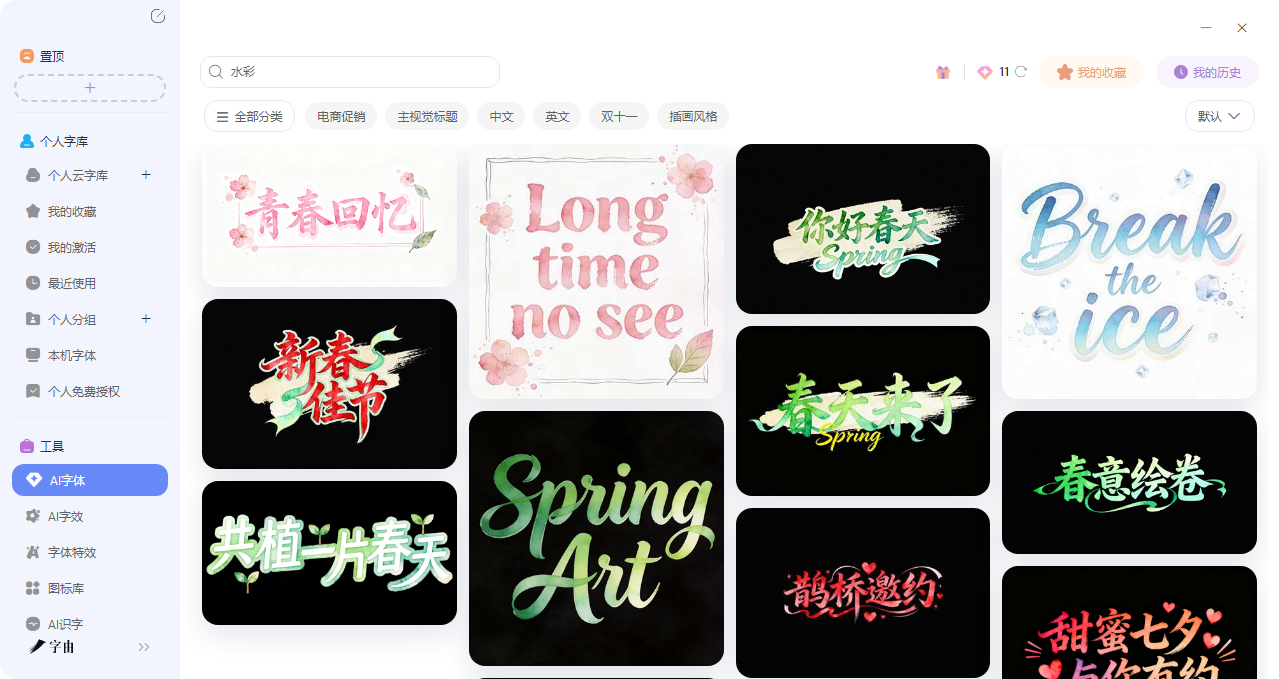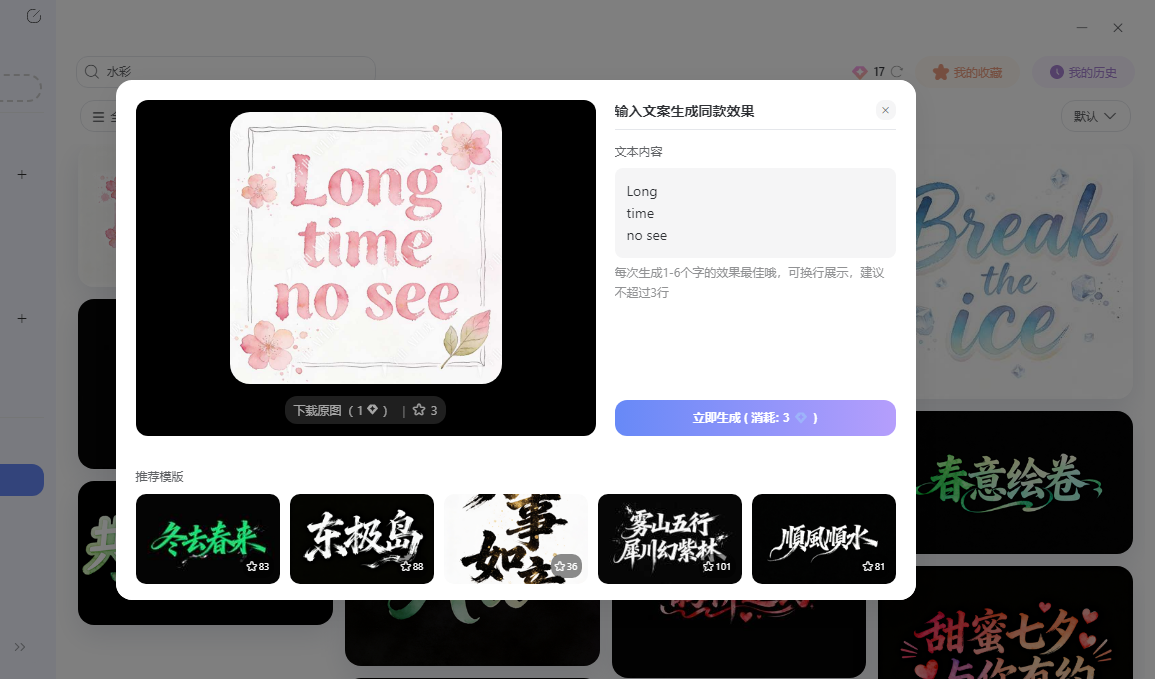
想要水彩感字体?试试这5个水彩风格文字设计工具
如果你经常做手账的话,肯定少不了一些水彩元素,这种像画在纸上的文字,总能让普通的画面多一层温度和质感。但是众所周知水彩字在纸面上容易写,但是怎么样才能转成电子版呢?自己画吧,没那个功底;找现成的吧,又怕版权不清。其实现在已经有很多水彩风格文字设计工具,能帮你一键生成这种效果。在这篇文章里我会推荐给大家5 个亲测好用的水彩风格文字设计工具,需要的可以收藏。
第一个要推荐的水彩风格文字设计工具是字由。除了本身拥有超过3500+款免费字体以外,字由还有很多实用的AI 工具,其中就包括AI 字体。它的“AI字体”功能,专门用来生成各种风格的艺术字,水彩效果当然也在其中。
下面是具体的生成步骤:
第一步:打开字由客户端,左侧导航栏找到【工具】→【AI字体】,或者从首页【字体工具】→【AI工具】进入。这个功能内置了大量艺术字模板,其中就有我们需要的水彩/手绘效果。
第二步:进入AI字体页面后,在搜索框里输入“水彩”“手绘”“晕染”“水痕”“手写感”等关键词,系统会自动筛选出所有带水彩质感的模板。你也可以直接点进“手写体”等分类里翻。
第三步:选择自己喜欢的模板,搜索结果会展示各种水彩风格的预览图,比如:
- 水彩晕染效果(边缘模糊,像颜料在纸上慢慢渗开)
- 湿笔触效果(带着水痕和笔触感)
- 干刷效果(像半干的画笔扫过纸面)
- 水彩肌理效果(能看见纸纹和颜料颗粒)
- 手绘水彩字(模仿真实手写的笔触)
每一个模板都有预览图,可以选择你喜欢的一个来生成。
第四步:点击选中的模板,进入编辑页面。在输入框里填你想要生成水彩效果的文字(比如“春日来信”“温柔以待”“手账时光”)。需要注意的是,可以看一下文字输入框的下面的提示词,每次生成1-6 个字的效果最佳!
第五步:确认文案后,点“立即生成”,等20-30秒左右,系统就会输出设计好的水彩艺术字图片。生成后可以预览效果,不满意就换其他模板再试。
这整个过程不超过五分钟,生成甚至不需要一分钟就可以做完了。如果你不满意,也可以去试试AI 字效或者是字体特效,都有足够丰富的模板库可供你选择!
2、FONTGET
我是直接在这个字体网站里搜索了“Watercolor”这个关键词,这样可以找到大量水彩风格的字体。它的分类逻辑很清晰,左侧有各种风格标签,方便筛选。
虽然这些不算严格意义上的水彩特效字体,但是这些字体的写法就能看出带着复古手写感,很适合做水彩效果。如果拿来作为设计的底层字体会非常合适,而且每款字体都标注了“100% Free”,可以放心下载。
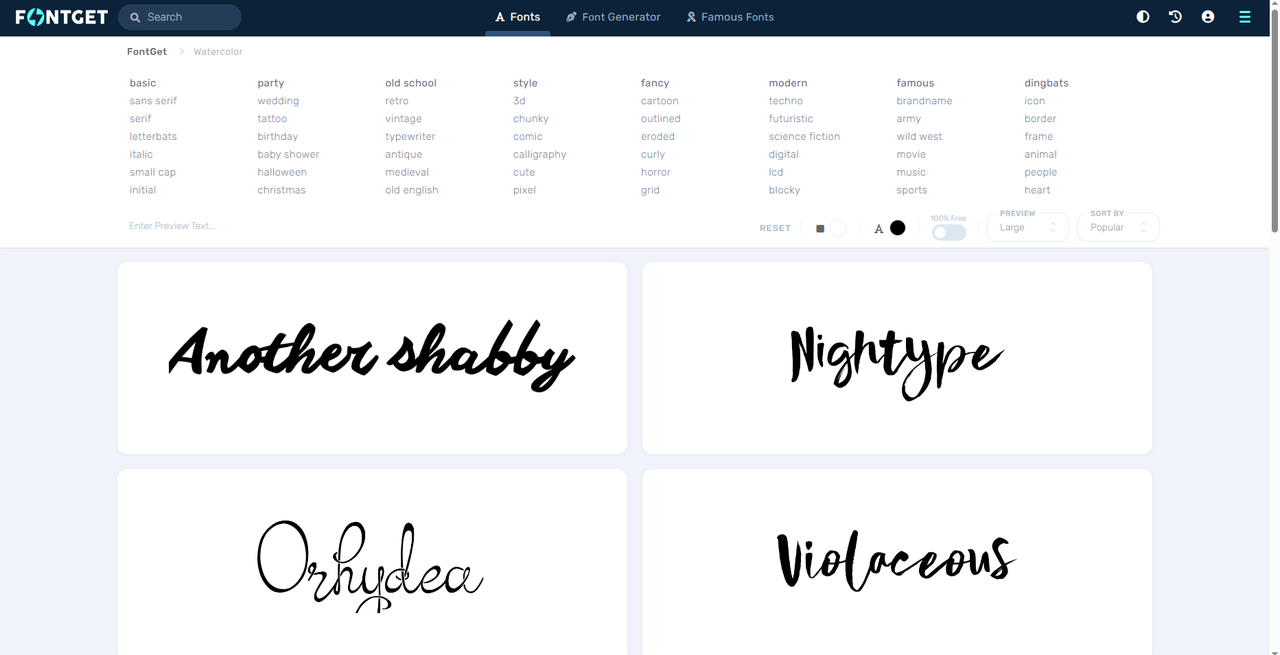
3、Envato Elements
Envato Elements 是一个专业的设计资源平台,它的水彩字体分类非常丰富。最主要的是这里的水彩字体不仅数量多,而且品质很高。我可以为大家推荐几款这里面质量比较高的水彩字体:
- Katie Roze Watercolor SVG Font:SVG格式的水彩字体,保留矢量特性的同时有水彩质感。
- Dayanara watercolor serif svg:衬线体的水彩版本,优雅温柔。
- Spring Rain:标注为“A TEXTURED BRUSH FONT”(带纹理的画笔字体),包含SVG和实心两个版本。
除了这几个之外,网站还提供了详细的筛选功能:可以按分类(Serif、Sans-Serif、Script)、字宽、最佳用途等筛选。虽然大部分是付费资源,但品质确实高,适合对水彩字体有专业需求的用户。
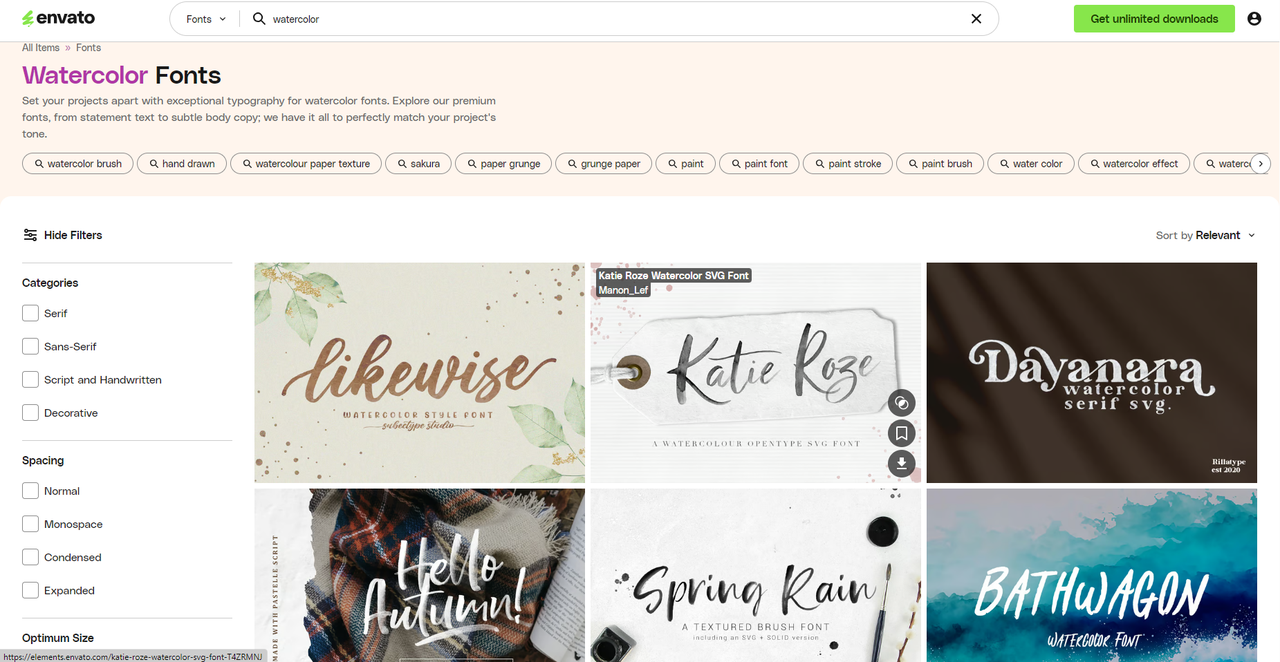
4、Creative Fabrica
Creative Fabrica 是一个创作者集市,收录了大量水彩风格字体,一共有2900+款水彩字体,网站支持预览功能,可以输入自己的文字,选择24pt/36pt/48pt/72pt等字号预览效果。虽然大部分需要付费,但偶尔有限免和折扣,可以关注。
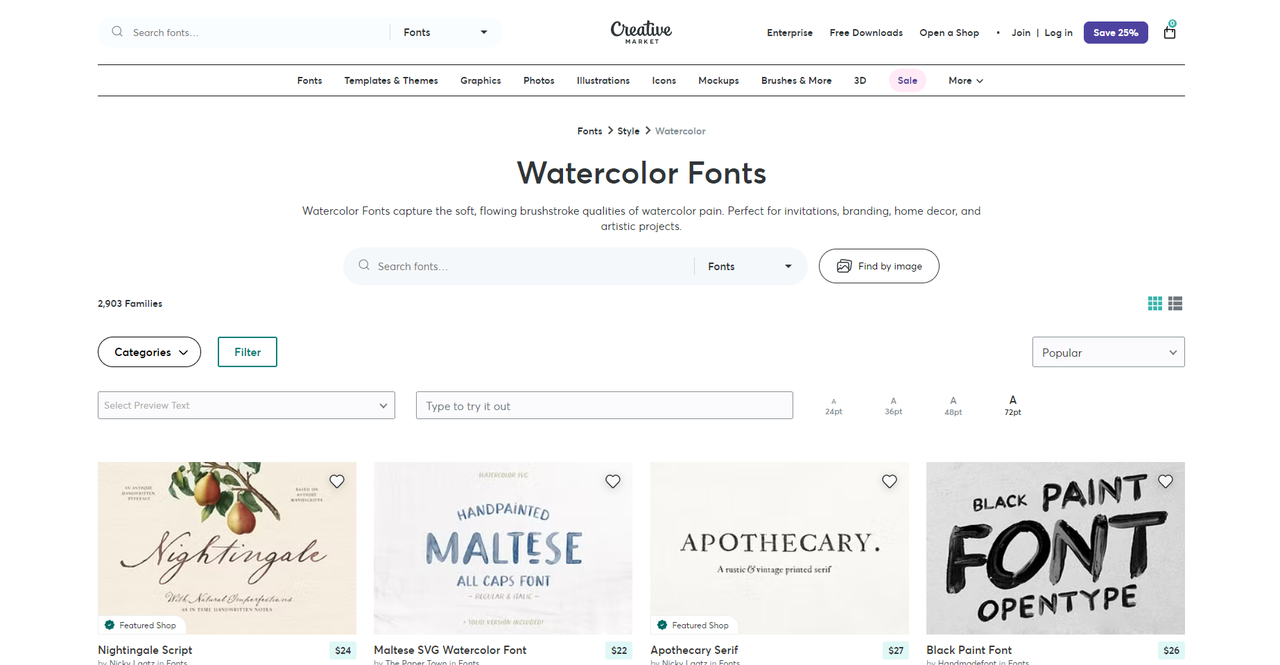
5、水彩字体合集站
最后一个网站更像是私人建立的水彩字体网站,目前可以看到比较热门的水彩字体有:
- Mongnai Script Font:水彩手写体
- Watercolor Font:直接以水彩命名的字体
- d Datang Font:可能是大唐体?适合国风水彩
- Fluid Font:流动感字体
- Strained Font:纹理感字体
这个网站的特点是字体都打上了“Watercolor”标签,方便集中浏览。每款字体都有对应的下载链接。
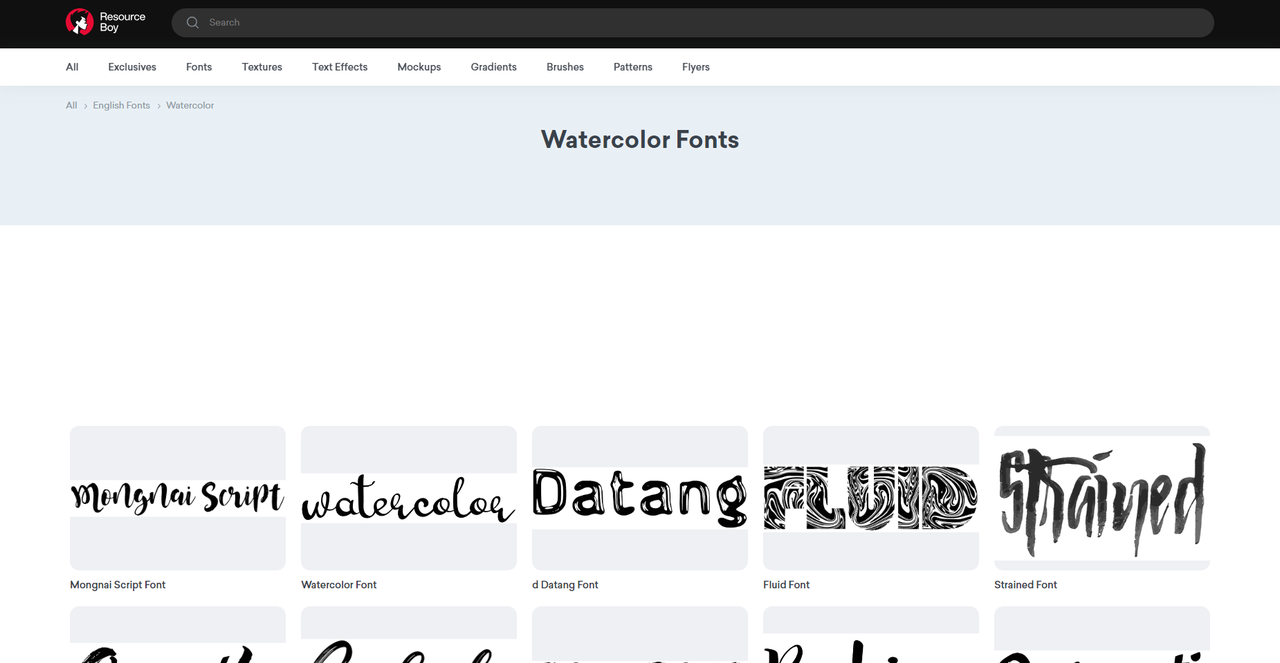
水彩风格文字的魅力就在于它有手写的温度,看着那几个字,你仿佛能看见颜料在纸上慢慢晕开,能感受到画笔扫过的痕迹,用在特定的设计上会很优雅,以前要这种效果肯定要靠手绘又或者是靠扫描然后一点点修图,现在有了这些水彩风格文字设计工具,你只需要输入文字,选个模板,等几十秒,就能拥有自带水彩质感的艺术字,字由对我来说就是完成这套流程的最佳选择,如果你也想让设计变得如此简单,可以试试字由。